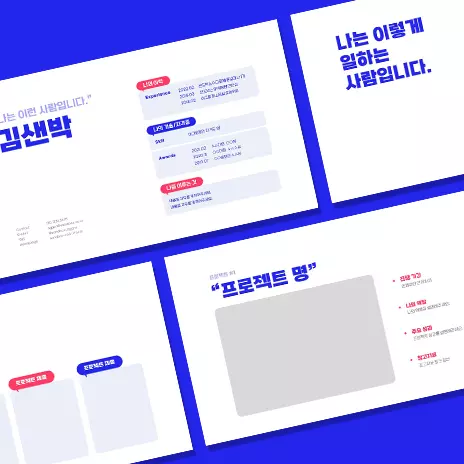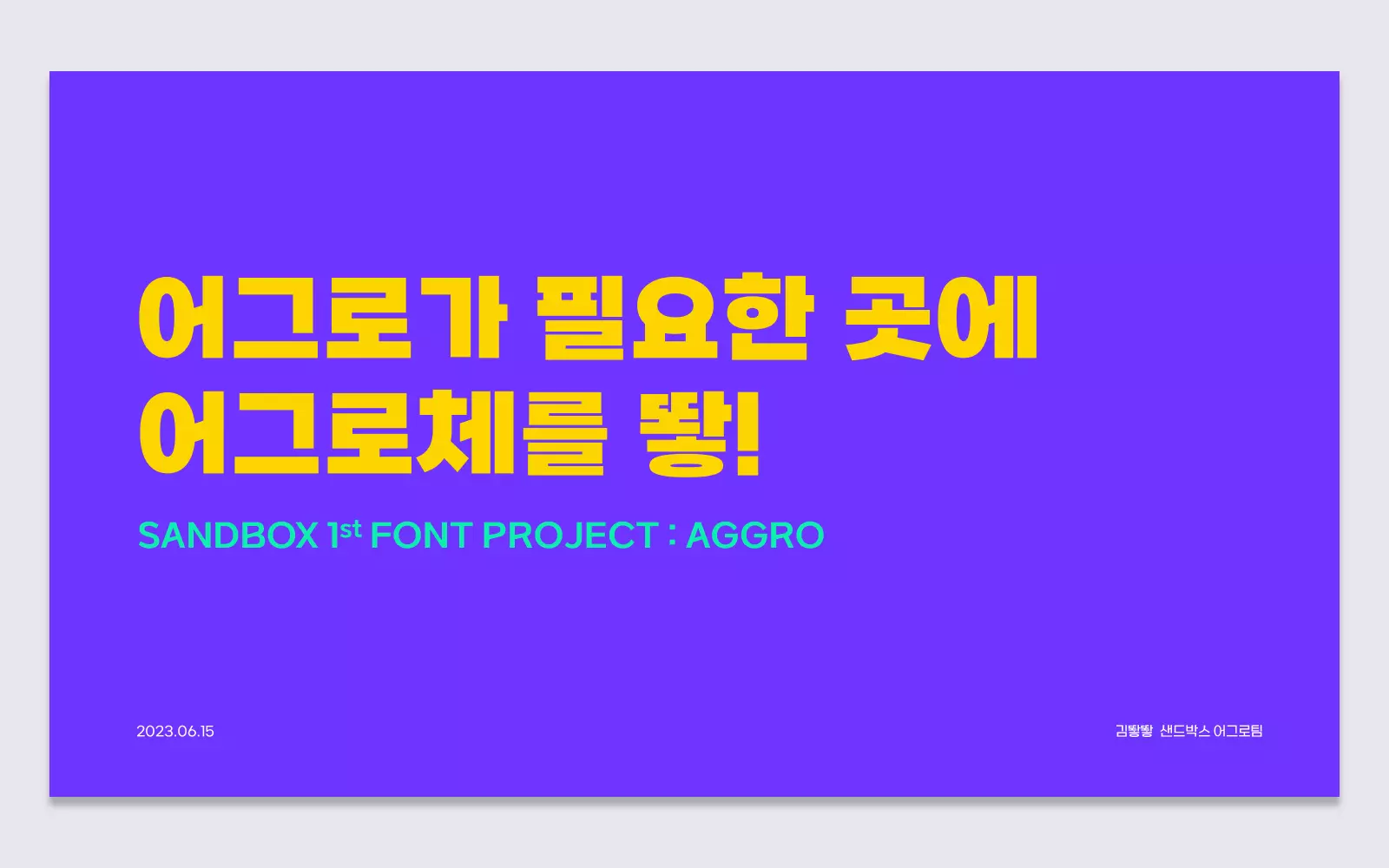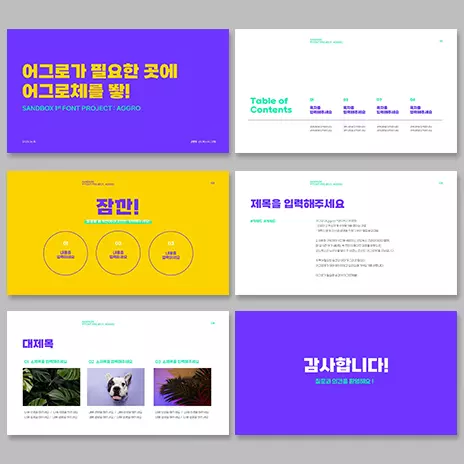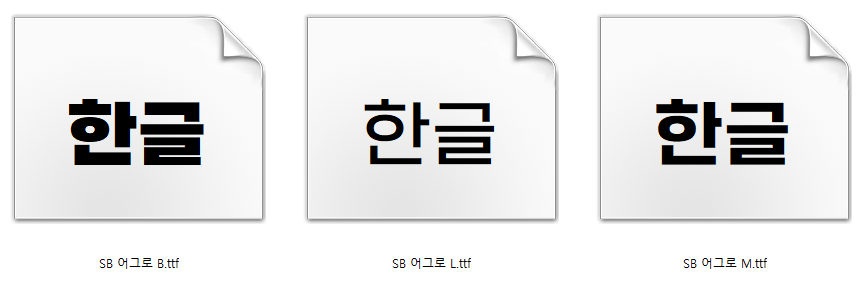
위의 이미지에서 보듯이 샌드박스 어그로체는 뙇이란 글자에서 느껴지는 어그로 즉, 독특한 곡선과 사선의 조합으로 선명하고 확실하게 주목받기를 원하는 마음 그대로를 표현한 글꼴이다.
해당 샌드박스 어그로체는 글자 글자마다 느껴지는 어그로체만의 매력이 명확하고 선명한데, 높이와 폭에서 특유의 리듬감을 발산하고 있다. 특히 새와 ㄷ을 조합할 때 나오는 이 스터에그가 곳곳에 숨겨져 있어서 이를 발견하는 재미도 쏠쏠하다.
즉, 샌드박스 어그로체는 한 가지 폰트인데 굵기만 변화를 준 3가지 글꼴 형태이다. 만약 맥용 운영체계를 지닌 컴퓨터 또는 그래픽 작업과 같은 고해상도 작업에 이용하려면 위에서 언급한 OTF 포맷을 다운로드해서 활용하면 된다.